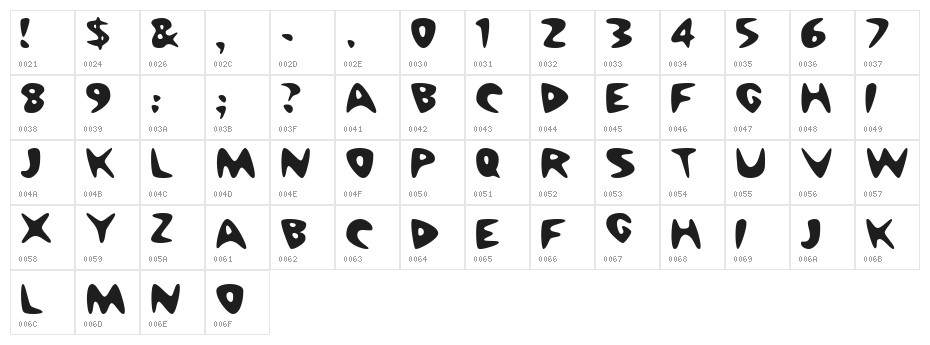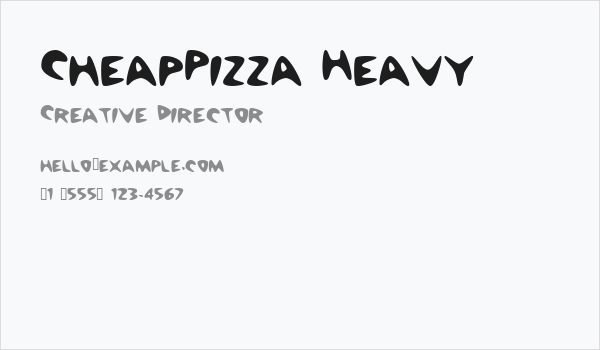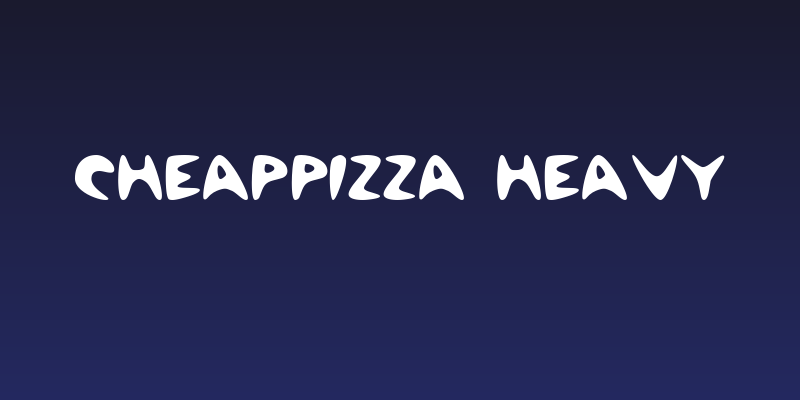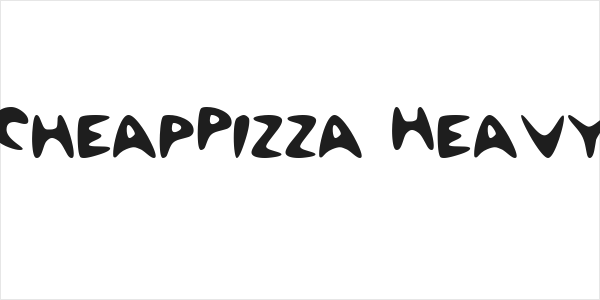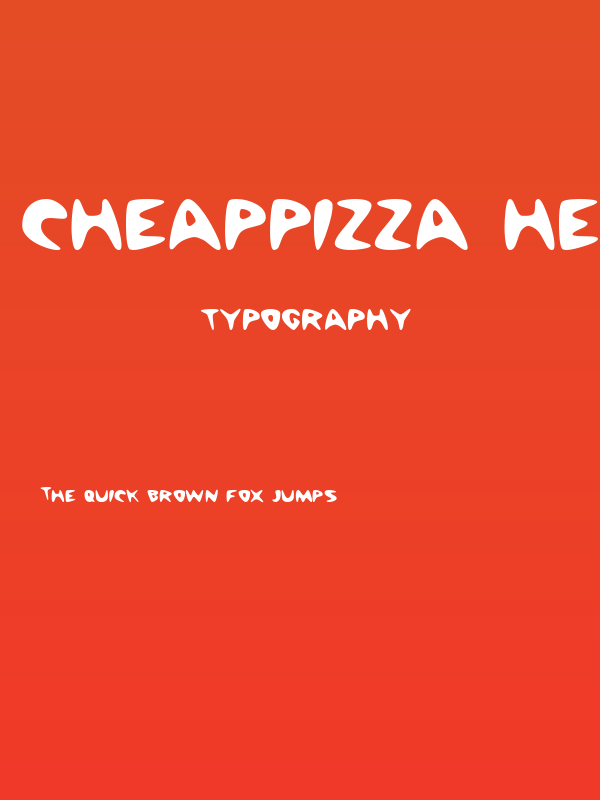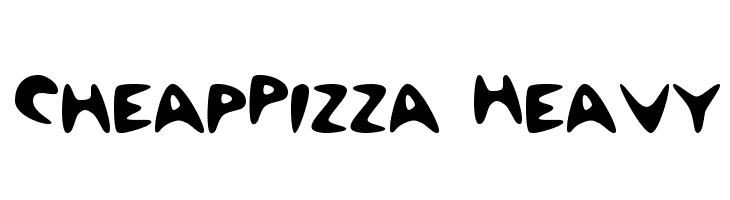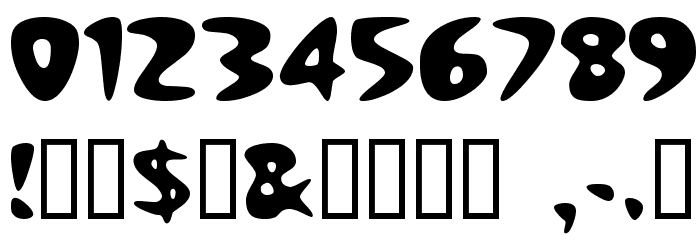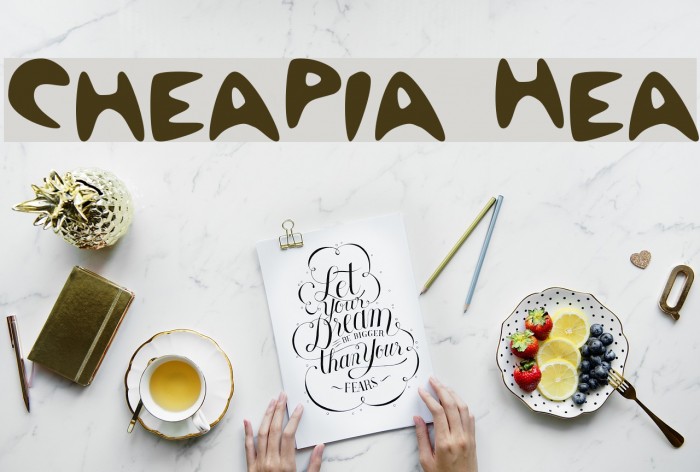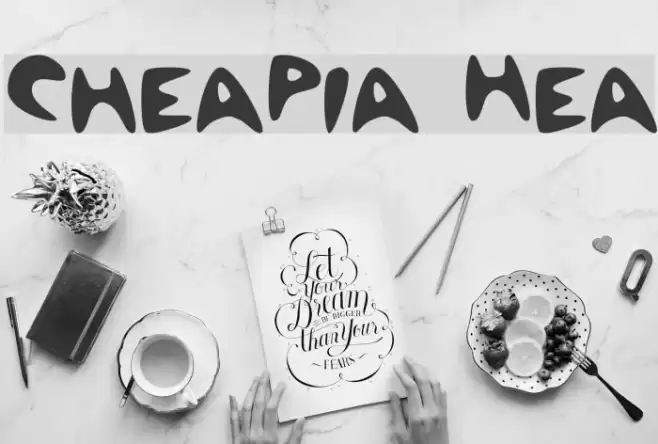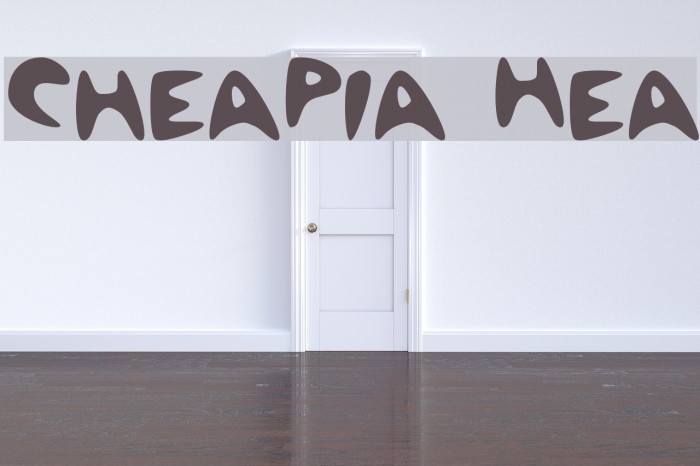
CheapPizza Heavy Font
| 全体的なスタイル | Playful, Whimsical |
| おすすめプロジェクト | Ideal for children's books, playful branding, party invitations, and creative posters. |